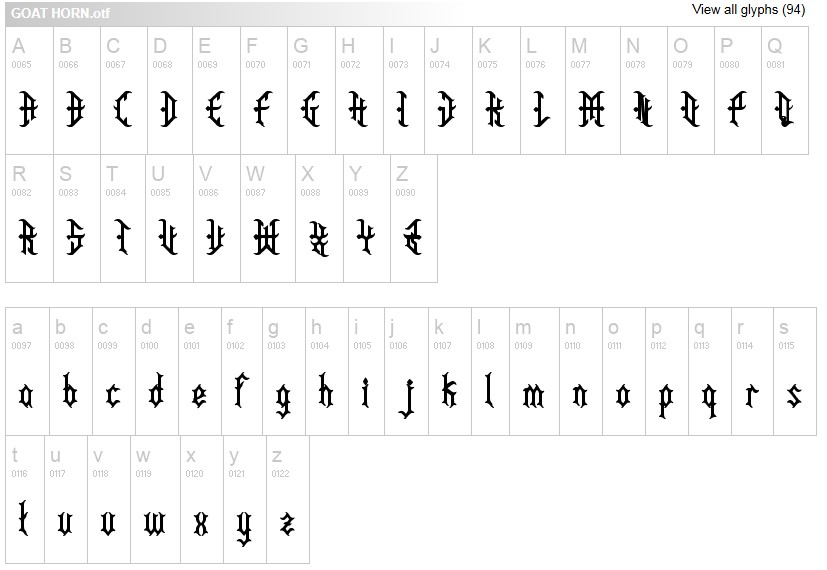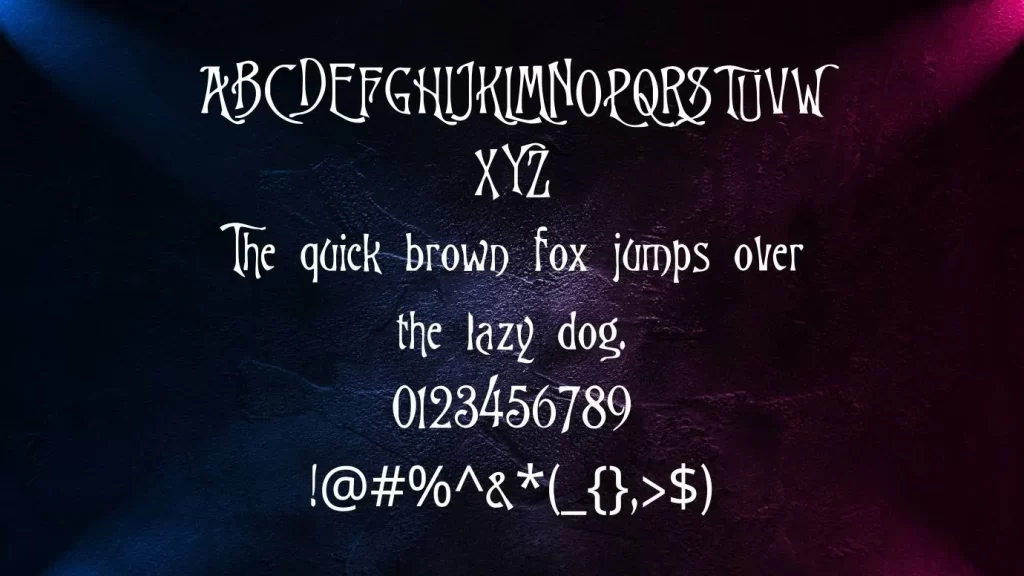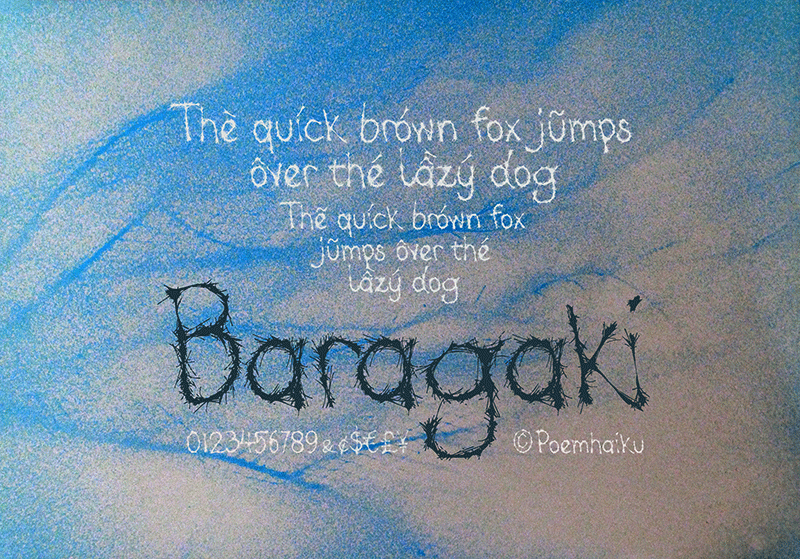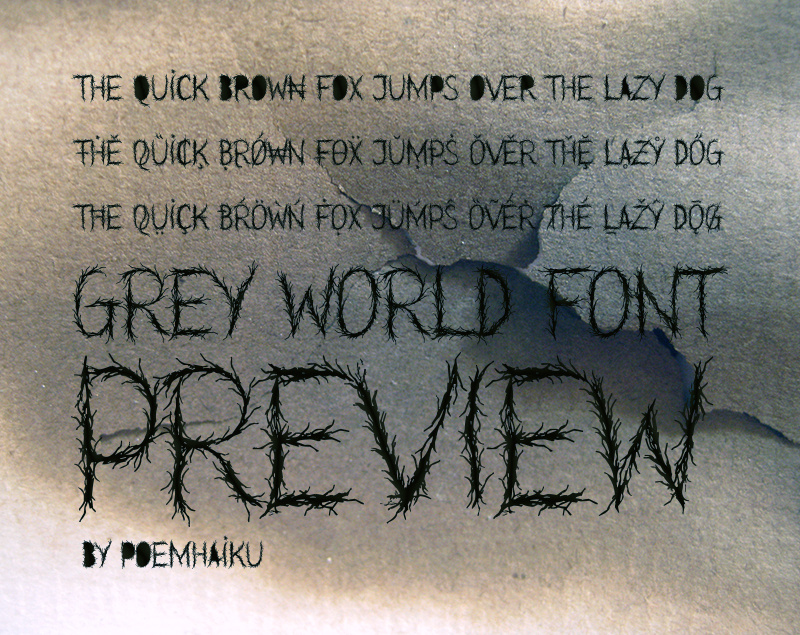
Trong mọi ấn phẩm, font chữ là yếu tố cực kì quan trọng, giúp truyền tải thông điệp của ấn phẩm. Và font chữ Halloween là yếu tố tốt nhất để truyền tải không khí rùng rợn, huyền bí của ngày lễ hội này.
Hãy cùng khám phá 13 font chữ halloween độc đáo và dễ áp dụng mà bất kì designer nào cũng có thể sử dụng để nâng tầm thiết kế của mình.
1. Tiêu chí chọn font chữ Halloween
Trước khi bật mí danh sách 13 font chữ halloween, chúng ta hãy xác định các tiêu chí lựa chọn để giúp bạn có được font chữ phù hợp nhất nhé.
- Phong cách ma mỵ, kì bí: Mùa Halloween luôn gắn liền với những font chữ với nét rạn nứt, góc cạnh, hoặc hình dạng khác thường, thể hiện không khí rùng rợn của Halloween.
- Khả năng dễ đọc: Dù font chữ độc đáo thế nào thì việc dễ độc vẫn là moojtp yếu tố cực kì cần thiết với bất kì ấn phẩm nào.
- Sử dụng linh hoạt: Hãy chọn các font chữ Halloween dễ thích ứng với nhiều loại thiết kế khác nhau, từ in ấn đến kỹ thuật số.
2. Tải ngay 13 font chữ halloween dành cho designer
1. October Crow
- Đặc điểm: Mang tính chất kinh dị thập niên 80, 90, truyền thuyết gothic (Phong cách thời trang Gothic xuất phát từ văn hóa Gothic, đây là một phong cách tôn vinh những điều bí ẩn, ma quái và quyến rũ) và mạng nhẹ. Lấy cảm hứng từ “The Crow” năm 1994, font chữ này được thiết kế hoàn hảo để sử dụng cho thiệp chúc mừng, lời mời dự tiệc Halloween và bất kì nhu cầu thương mại nào.
2. Halloween Too
- Đặc điểm: hiệu ứng chữ máu nhỏ giọt, phù hợp với thiết kế theo chủ đề kinh dị. Font chữ viết tay cũng có chữ in hoa và chữ thường, ứng dụng linh hoạt.
3. Goat Horn
- Đặc điểm: Font chữ theo phong cách gothic này có chất lượng cao, tinh tế nhưng cũng có gì đó hơi ma quái. Các chữ cái hoa cong khá đẹp mắt, mang đậm chất gothic.
4. Earwig Factory
- Đặc điểm: Nhìn font chữ Holloween này bạn sẽ liên tưởng tới ngay 1 bộ phim kinh dị đầy bí ẩn. Các chữ cái lộn xộn được gắn trên các tấm bìa nền, giống như các lá thư đòi tiền chuộc trong các bộ phim trinh thám – kinh dị.
5. Nightmare 5
- Đặc điểm: Phong cách áp phích cổ điển, chữ cái ma quái cô đọng. Tuy nhiên nếu sử dụng cho mục đích tiếp thị, bạn cần mua giấy phép thương mại nhé.
6. Creepster
- Đặc điểm: Font chữ Halloween cực kì đa năng. Nó là một font chữ retro, thể hiện rõ sự bí hiểm, làm cho ấn phẩm thiết kế trở nên đáng sợ hơn.
Những font chữ kì quặc giúp thiết kế Halloween của bạn độc lạ hơn
7. Alice in Wonderland
- Đặc điểm: Lấy cảm hứng từ bộ phim “Alice ở xứ sở thần tiên” của Tim Burton. Nó có thể không hoàn toàn là font chữ Halloween, nhưng nếu đã xem Alice ở xứ sở thần tiên, bạn cũng thấy sự sợ hãi và phép thuật kì quặc trong đó. Nó cũng rất phù hợp với thiết kế Halloween của bạn.
8. Burton’s Nightmare
- Đặc điểm: Font chữ được lấy cảm hứng từ Burton, mang tính trang trí. Nó bao gồm cả chữ thường và chữ hoa, bạn có thể ứng dụng linh hoạt khác nhau. Nó chắc chắn sẽ giúp thiết kế của bạn hoàn hảo hơn.
9. HalloWitchZ
- Đặc điểm: Font chữ độc đáo phù hợp với các thiết kế theo mùa, nó gợi nhớ tới những bìa sách phép thuật và tiểu thuyết. Kích thước và độ lớn khác nhau của chữ cái làm cho HalloWitchZ trở nên vui tươi và khó đoán, mang lại sự thú vị cho người xem.
Font chữ Halloween Việt hóa
10. Twisted Halloween
- Đặc điểm: Không quá nhiều thiết kế phá cách, nhưng sự gọn gàng, nét chữ nhọn khiến tạo nên cảm giác lạnh lẽo khi nhìn vào thiết kế. Nó cũng mang đến sự pha trộn giữa ma quái và quyến rũ cổ điển.
11. Biometric Joe
- Đặc điểm: Giống font chữ máy đánh chữ hồi xưa, mang cảm giác hoài niệm, có chút gì đó hơi quái dị, bí ẩn và tạo nên sự sợ hãi.
12. Are You Serious
- Đặc điểm: Các chữ cái xoắn đuôi, gợi nhớ đến thế giới phù thủy. Bạn có thể sử dụng linh hoạt trong các ấn phẩm social.
13. Baragaki
- Đặc điểm: Nét chữ nguệch ngoặc như những chiếc gai nhọn, khiến người xem có cảm giác rợn tóc gáy. Với font chữ này, đảm bảo tính dễ đọc, bạn có thể sử dụng cho 1 đoạn văn dài.
4. Kết luận
Việc lựa chọn font chữ phù hợp có thể mang lại hiệu ứng bất ngờ, tăng hấp dẫn và ấn tượng cho bất kì thiết kế Halloween nào. Hy vọng với những gợi ý font chữ Halloween trên đây, các bạn có thể linh hoạt ứng dụng vào các ấn phẩm thiết kế khác nhau của mình.